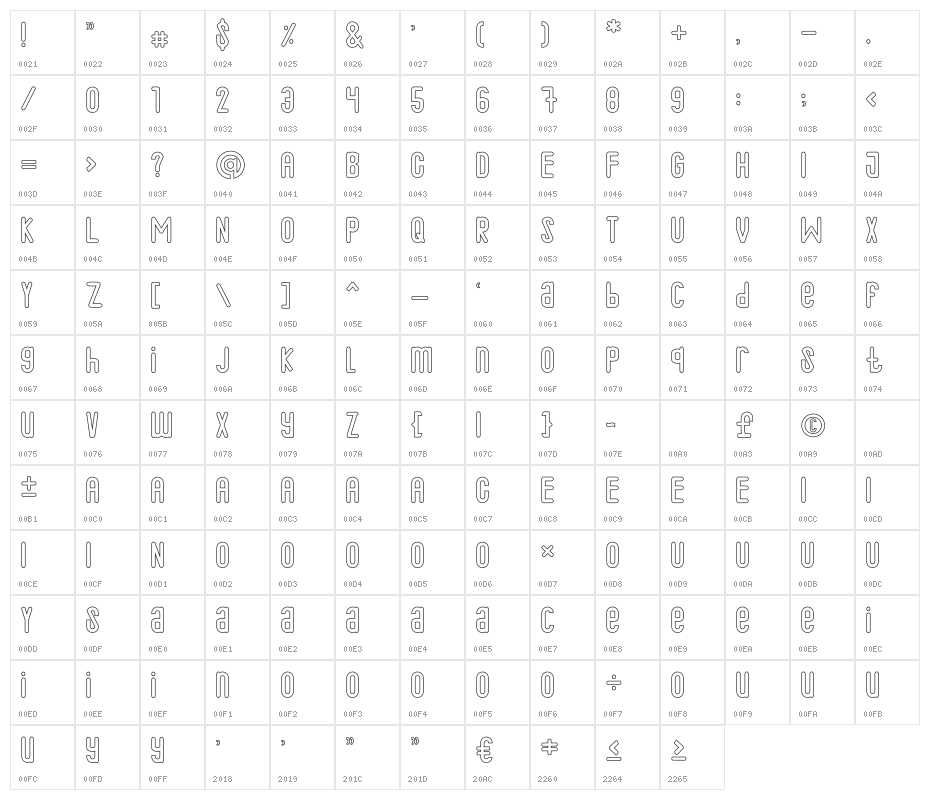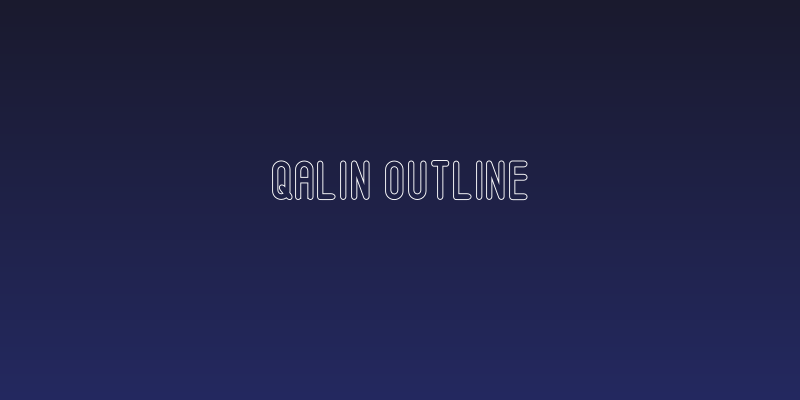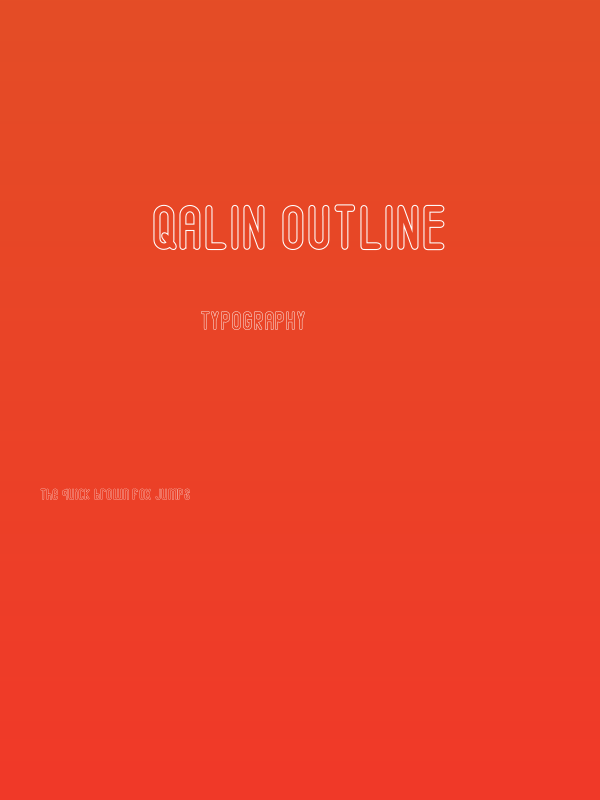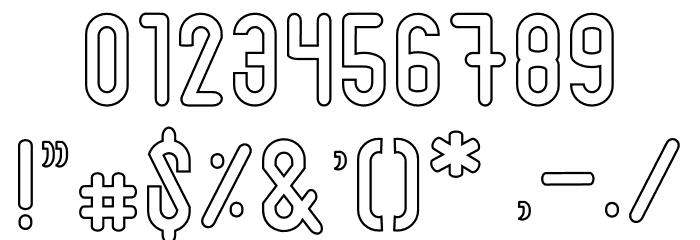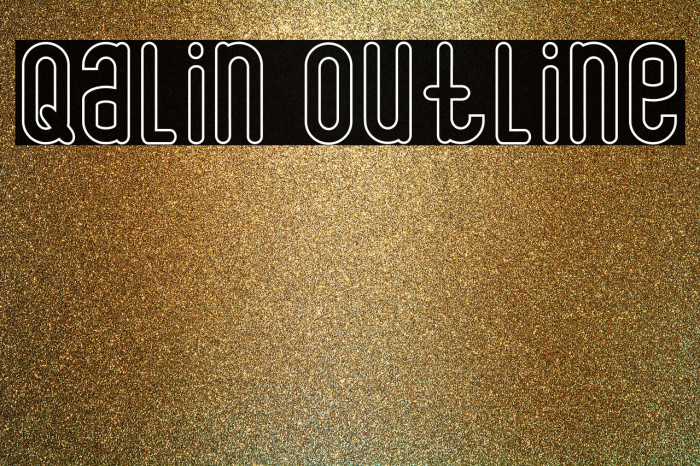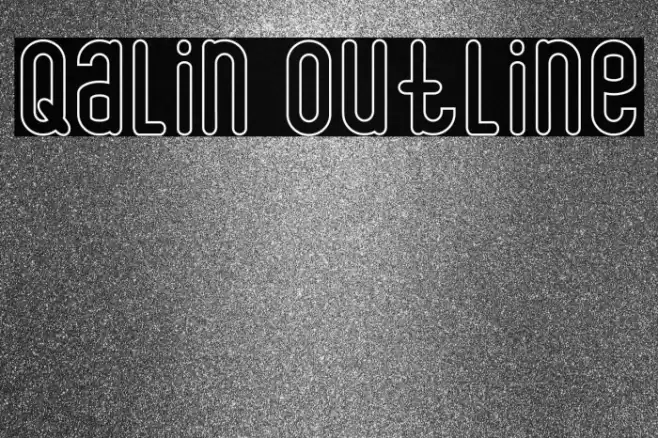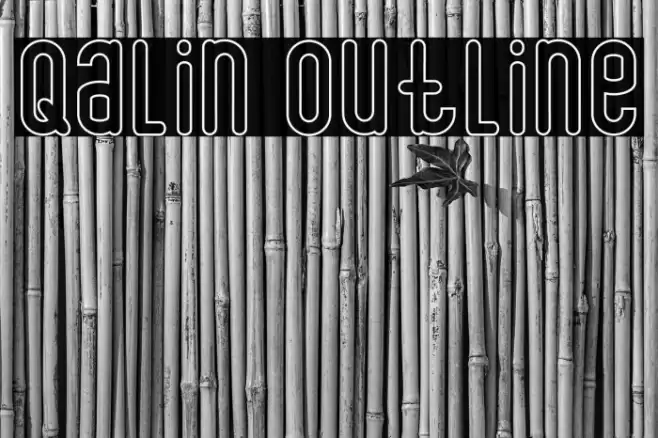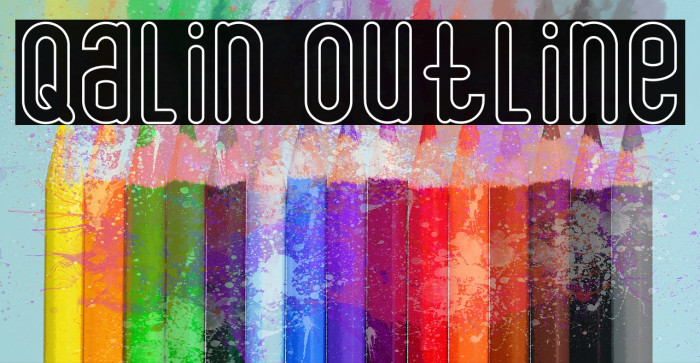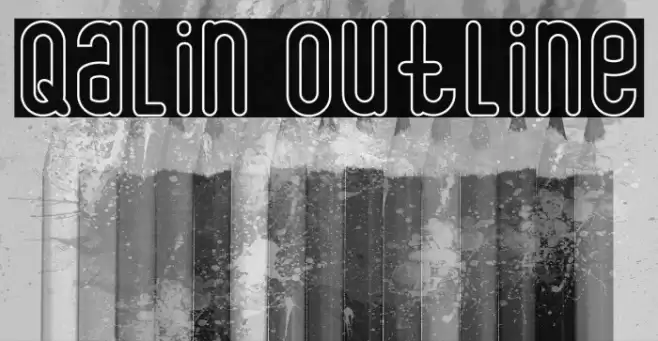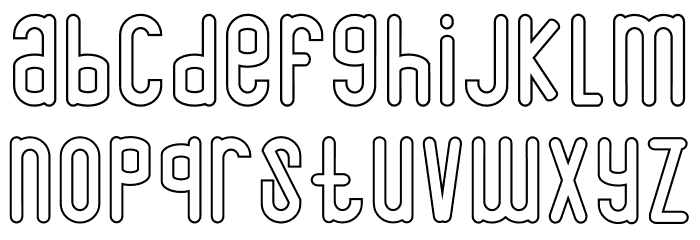
Qalin Outline Font
| Proiecte propuse | Ideal for branding, posters, headlines, and digital media where a modern and stylish appearance is desired. |